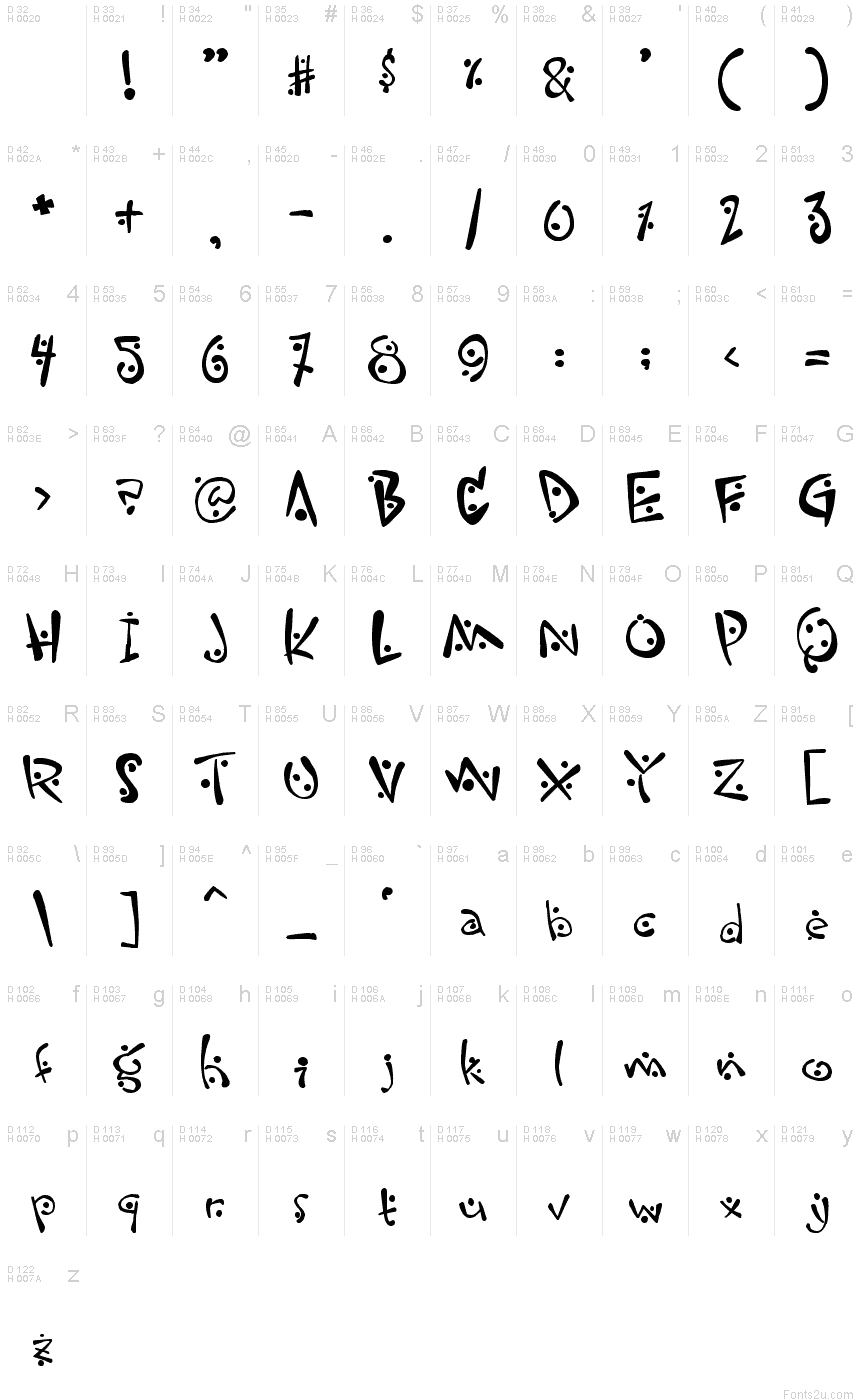
Zitcream od Jakoba Fischera je bezplatné, ručně kreslené titulkové písmo s uvolněným dojmem, jako by bylo psáno fixou. Písmena se záměrně vlní a kombinují silné tahy, kulaté tečky a křivolaké tvary, což celému písmu dodává ležérní, hravý a trochu nezbedný charakter.
Skvěle zapadne do komiksových titulků, na obálky dětských knížek, kaviarenské tabule, hravé obaly nebo plakáty ve stylu koláží, kde právě tento nepravidelný rytmus udržuje lidský dojem. Jako bezplatný font funguje Zitcream dobře i na krátké nadpisy nebo rychlé brandingové poznámky – zejména ve chvíli, kdy chcete, aby text působil jako ručně načmáraný, a ne příliš strojený.
Zitcream